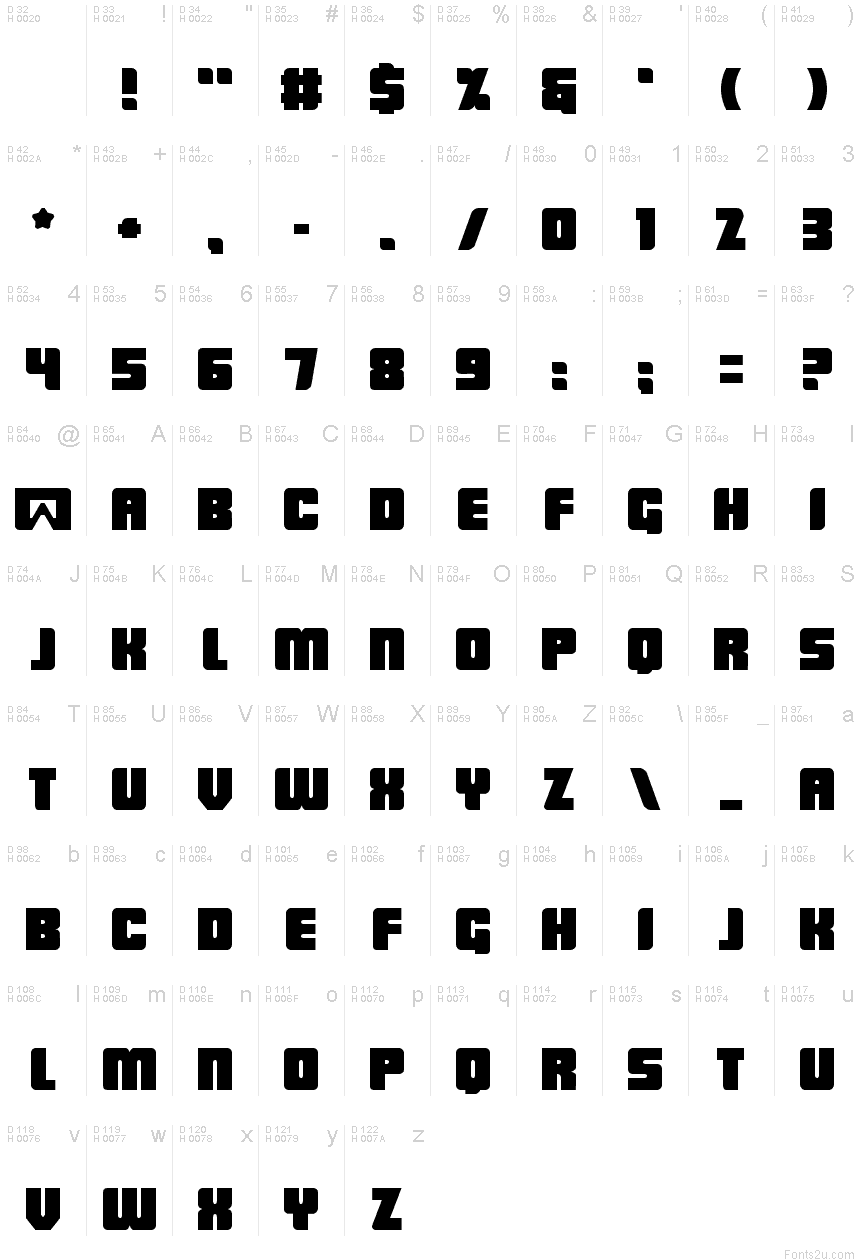
LowRider BB autorstwa Nate'a Piekosa to darmowy krój typu display o zaokrąglonych, blokowych kształtach i zwartym, przysadzistym rytmie. Litery mają szerokie, kwadratowe formy z miękkimi narożnikami i głębokimi wycięciami, co nadaje projektowi solidny, autorski charakter, unikając przy tym ostrego czy mechanicznego wyglądu.
LowRider BB świetnie sprawdza się w logotypach sklepów rowerowych, grafice streetwearowej, tytułach na plakatach, okładkach albumów i ulotkach wydarzeń, ponieważ jego masywne kształty tworzą wyrazisty znak graficzny. Ten darmowy font pasuje również do niestandardowych szyldów i brandingu w stylu gier, gdy potrzebujesz liter, które są niskie, szerokie i stworzone do efektownych nagłówków.